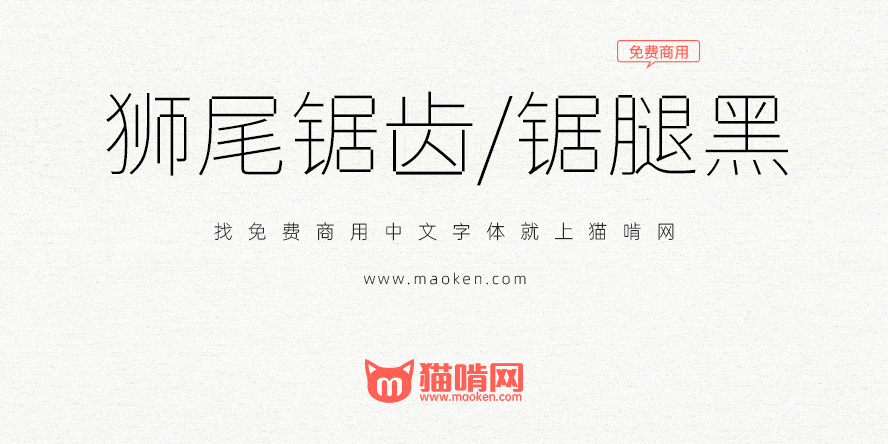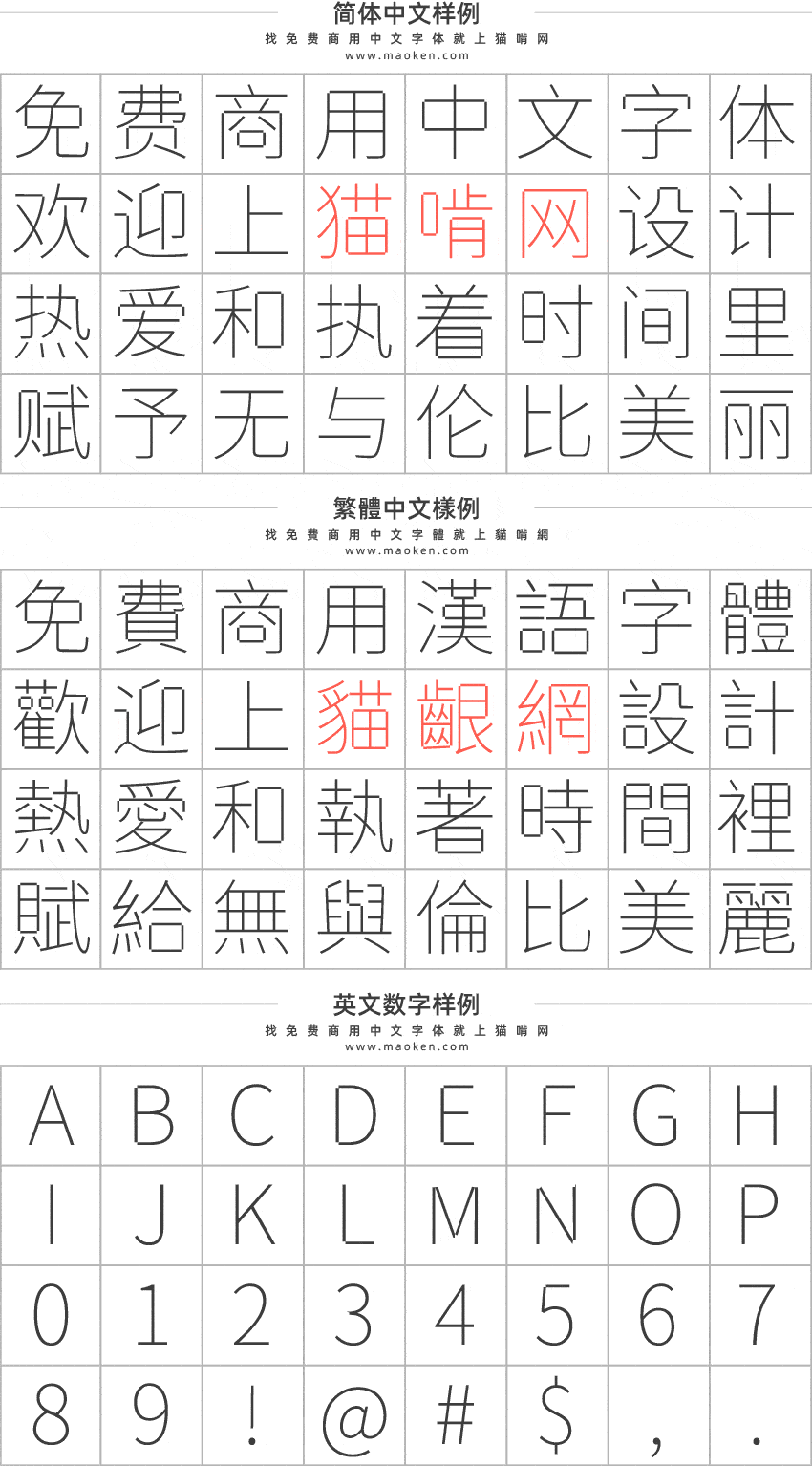
狮尾锯腿黑体和狮尾锯腿黑体是基于思源黑体的转角挖空改造,更加简明现代化的字体。支援简体中文、繁体中文、韩文与日文;可以免费商用,欢迎大家自由应用、自由优化、自由改作!
狮尾锯齿黑体和狮尾锯腿黑体的特色是转角挖空,文字产生锯齿状的效果。有些文字没有处理的很好看,丑丑的。
「狮尾锯齿黑体」与「狮尾锯腿黑体」差别在有没有拔脚,「拔脚」就是会有较少的笔画,例如移除「口」字的左右下角会多出的短线条。有拔脚的字会较圆,但是会造成有些字因直接去掉腿后左右不平衡、左右不对衬的「悬空」问题。改使用「腿」系列字体就不会有这个问题。
少發布這種AI隨便計算亂改一通,沒有美學的低級製品吧;
或者是重新找個板塊發布這種「Font」;
因為AI深度學習工具的普及,字型的開發雖然變得無比簡單,但是字型的設計卻是需要字體設計師深厚功底的領域,如果放任這種低級製品(今天改個圓角,明天搞個邊角預設,後天搞個倒角)無限制的開發,大部分設計師/公司為了省錢使用這種「免費字型」,我們的設計環境會變成什麼樣子?
歡迎有一定美學能力的程式設計師製作有價值的AI字型(比如台北黑體、未來熒黑、更紗黑體、昭源黑體、全瀨體等)
其實這些修改的字體,也有一部分用戶是有這種需求的。特別是不是專業做設計的人羣,可能衹是需要做PPT或者Keynote等,他們如果需要實現這種樣子比較困難,而有現成的字體則可以直接使用。不過貓啃網上的字體大全的分類的確是可以繼續優化,十分感謝您提出的寶貴的意見。
这款字体质量确实不高,不过MAX贡献过不少优质的字体,是值得肯定和赞扬的。字体开源的意义本就是大家发挥自己的创意想法修改和学习,最终才会诞生优质的字体。
字体是否低劣与否不能以你一个人的角度进行批判,网络自然会给予优胜劣汰,真正的低劣字体自然会被网友拒绝下载而被人遗忘。猫啃网作为免费字体网的领军网站,自然要包罗万象,字体优劣与否交给网友就可以。
最后给猫啃网一点建议,可以增加一个字体热度或者字体下载量排行榜,优秀字体自然靠前,劣质字体自然被人遗忘。
字体开源的本意是希望参与的成本变低,而不是设计的水准变低;昵图网的设计LOW到爆炸,但昵图网没有被淘汰,而也是因为昵图网的素材太LOW,导致街面最常见的设计很LOW;如果昵图网的设计素材质量高,底层设计水准就会变得更高;
其實MAX的字體目前都還停留在簡單的腳本程式轉換思源黑體字型,還沒有到AI深度學習的等級…。台北黑體似乎是純手工去修改,而且幾乎是直接使用思源黑體CJK KR 的版本。
赞同!说出了我想说的话,后面推出的思源改狮尾系列已经开始剑走偏锋了,如果这个社会充斥着大量没有美感、差异性低的免费字体,会造成使用混乱并且拉低效率。
你不喜欢这样的字体,你可以不下载不安装,这并不妨碍你设计工作。但你不能自私地认为所有人不需要这样的字体。
我就喜欢MAX的字体,他给我的工作带来了极大的方便。就算有一天猫官网不在收录,我也会去MAX的网站下载。
行业的进步和发展和行业的素质息息相关,因为任何行业都是金字塔形,而塔底的人才是行业的常态,如果行业一片都是狗屎,塔底的根本无从辨别好坏,新人是无法分辨字体的好坏的,带来的结果就是,社会上充斥着这种低级字体的设计;懂吗?